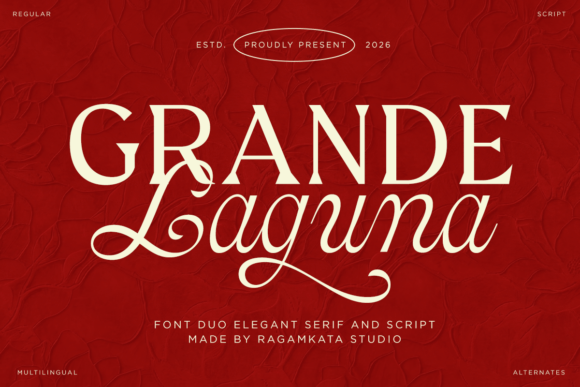
Grande Laguna
Grande Laguna와 같은 κ³ ν’ˆμ§ˆ μžμ‚°μ„ μ°Ύκ³  μžˆλ‹€λ©΄ 이 프리미엄 νŒ¨ν‚€μ§€λŠ” 창의적인 ν”„λ‘œμ νŠΈλ₯Ό μœ„ν•œ ν™˜μƒμ μΈ μ„ νƒμž…λ‹ˆλ‹€.
POD(μ£Όλ¬Έν˜• 인쇄) μ œν’ˆ, κ²°ν˜Όμ‹ μ΄ˆλŒ€μž₯ λ˜λŠ” μ†Œμ…œ λ―Έλ””μ–΄ κ·Έλž˜ν”½μ„ λ§Œλ“€ λ•Œ Grande LagunaλŠ” 이상적인 μ„ νƒμž…λ‹ˆλ‹€.